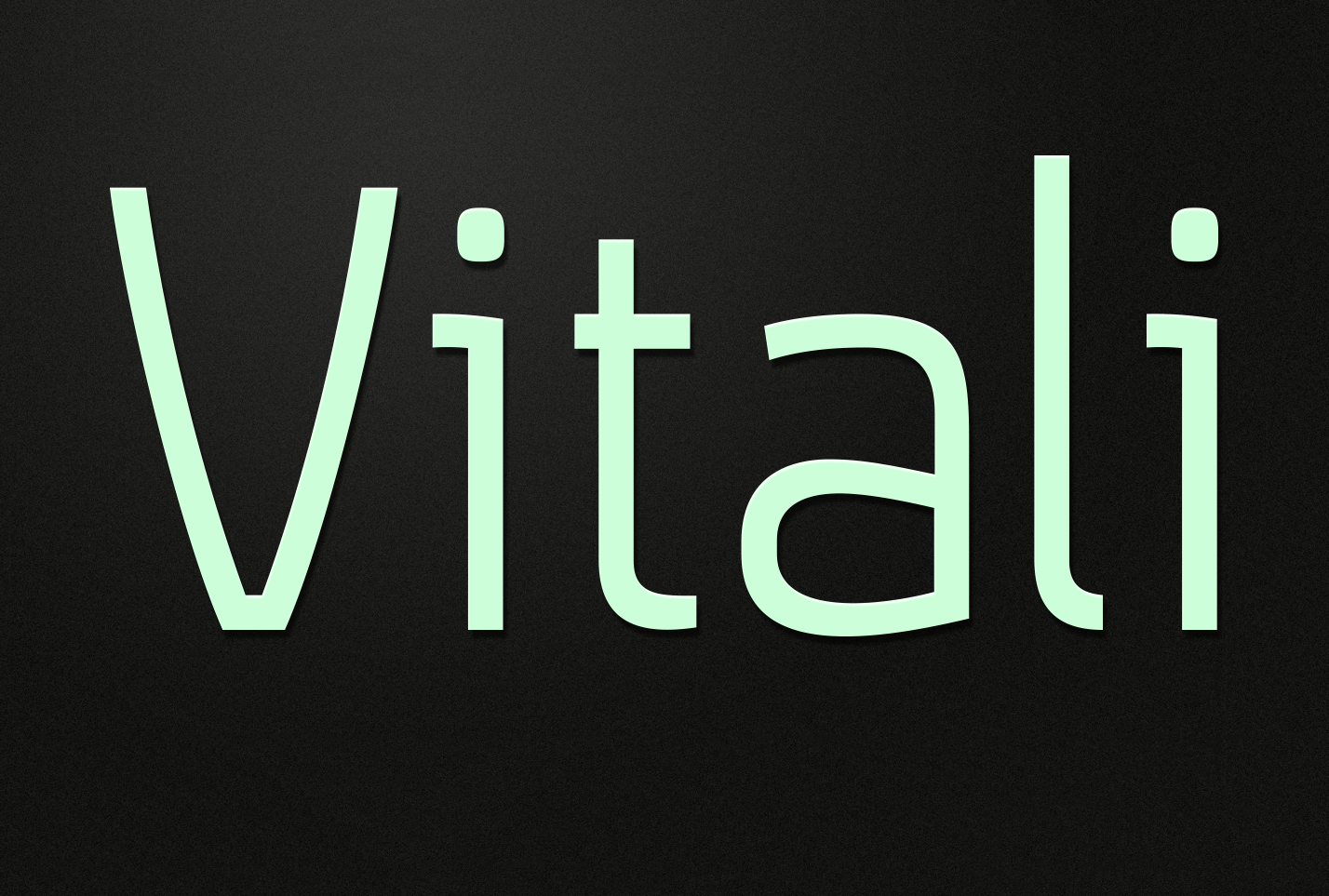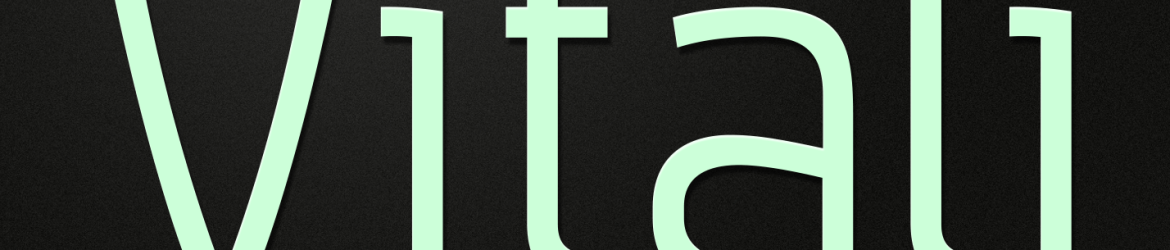
Vitali é uma variedade do meu último tipoface Aneba_family. Este é um tipo geométrico livre de traço com um feeling limpo e simples. Com sua baixa contraste e altura de x alta, Vitali é perfeito para textos longos e cabeçalhos. Essa família de fontes contém dois pesos em duas diferentes formas – bold e italic. A Vitali Family não só oferece flexibilidade estilística, mas também suavidade no uso da geometria pura do tipo. Ideal tanto para projetos profissionais quanto para publicações digitais, a Vitali é uma excelente escolha para quem busca um aspecto moderno e clean sem sacrificar a legibilidade.